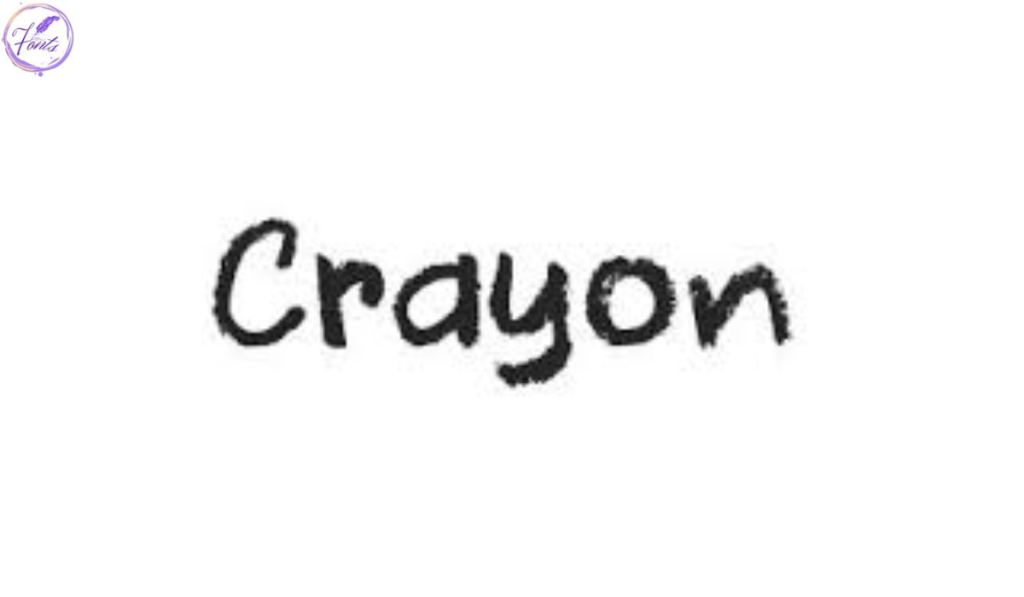
Crayon font việt hóa
Tác giả: Opentype Studio
Ngày phát hành: 2014
Ngôn ngữ: Tiếng Anh
Bộ Font: Pastel Crayon , Crayon
Phân loại: Cá tính, độc đáo
Kiểu chữ: Viết tay (handwritten)
Crayon font là một kiểu chữ tuyệt vời cho những ai yêu thích phong cách sáng tạo và vui nhộn. Được thiết kế bởi Opentype Studio vào năm 2014, crayon font mang đến cho người dùng những nét chữ mềm mại, giống như những nét vẽ bằng bút sáp màu. Với sự pha trộn giữa tính nghệ thuật và tính ứng dụng cao, crayon font dễ dàng thu hút ánh nhìn và truyền tải cảm xúc tươi vui.
Đánh giá crayon font
Crayon font đã nhận được rất nhiều đánh giá tích cực từ cộng đồng thiết kế. Điểm nổi bật của crayon font là khả năng Việt hóa hoàn hảo, cho phép người dùng sử dụng trong các dự án tiếng Việt một cách dễ dàng. Ngoài ra, crayon font còn được khen ngợi vì sự đa dạng trong ứng dụng, từ thiết kế thiệp mời, poster, đến các dự án giáo dục. Nếu bạn đang tìm kiếm một font chữ vừa đẹp mắt vừa dễ sử dụng, thì crayon font chính là lựa chọn lý tưởng.